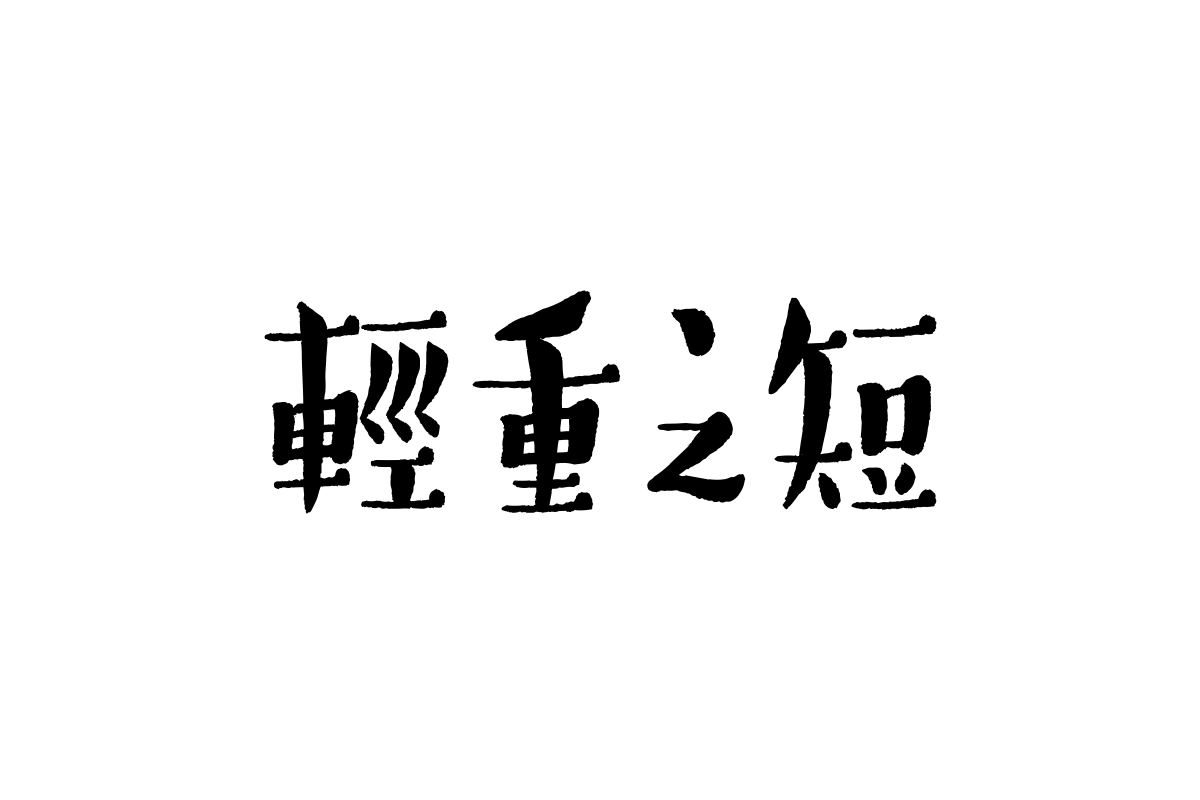
汉仪春机体基础版繁体是汉仪公司推出的一款中文字体,主要用于印刷、设计等领域。这款字体具有简洁、大方的特点,适用于各种商业、办公、广告等场合。
汉仪春机体基础版繁体采用了现代的设计理念,字形结构清晰,笔画流畅,易于阅读和识别。同时,这款字体也具有一定的艺术感,能够很好地融入各种设计元素,提升整体的设计效果。
此外,汉仪春机体基础版繁体还具有较高的可读性和可扩展性,可以根据不同的设计需求进行个性化定制。这使得它成为了设计师们非常喜欢的一款字体。
总的来说,汉仪春机体基础版繁体是一款功能强大、应用广泛的中文字体,无论是在印刷还是设计领域都能发挥出重要的作用。